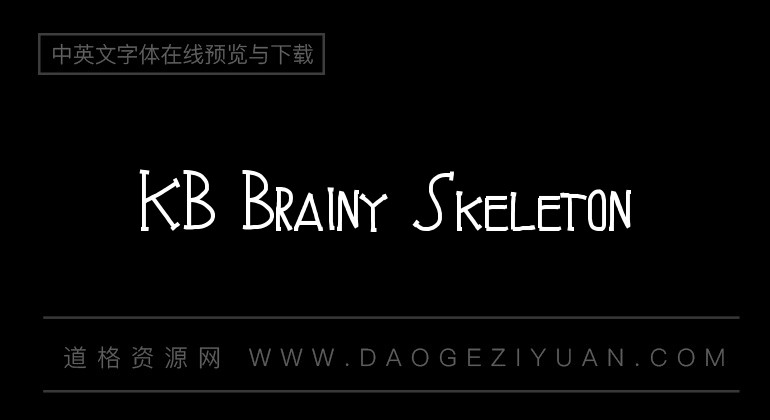
KB Brainy Skeleton
KB Brainy Skeleton 字体是一款字体设计,它使用了骨架设计,具有清晰的外观和简单的线条,可以提供一种显示效果,特别适合技术型文档,如代码,数学公式等。它还可以用于商业,技术,科学,社会学,文学,经济学,历史等学科的文档。它拥有超出常规字体的特点,可以更好地展示文档的细节。
KB Brainy Skeleton是一款非常不错的手写艺术字体,具有很好的视觉感,适合于文化类的宣传设计、商业类品牌的广告和产品包装设计以及个性化文字排版等较多场景。